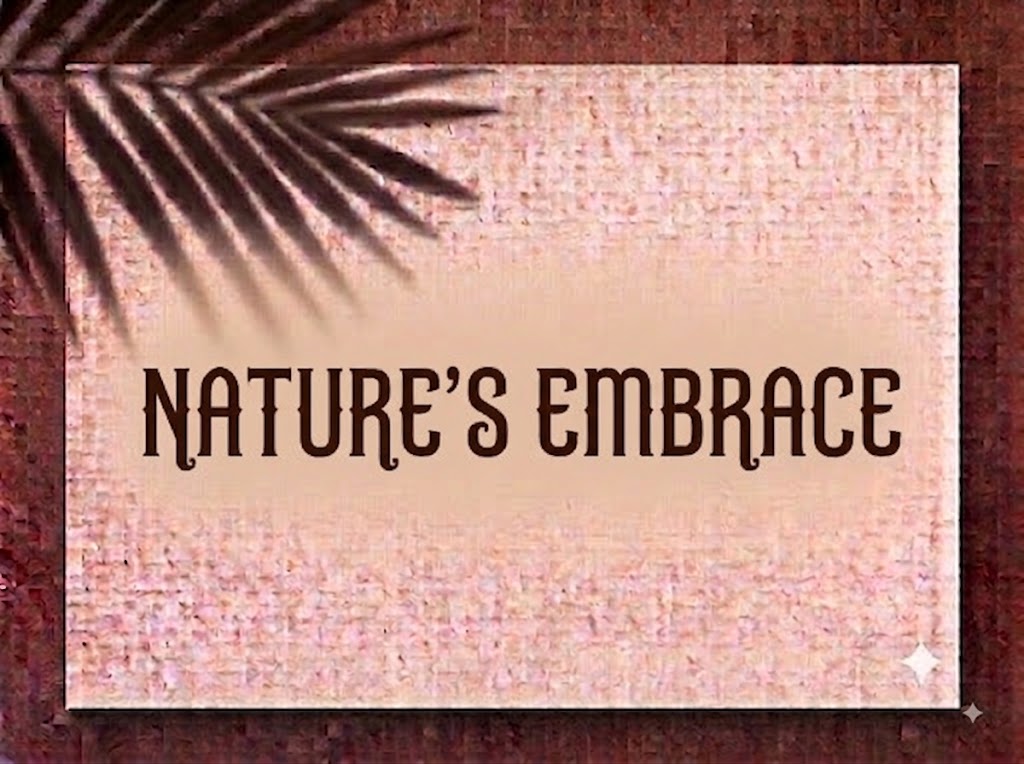
1FTV VIP Brownstone
Trong thế giới thiết kế đồ họa truyền thông và sáng tạo nội dung số, những bộ phông chữ Display mang phong cách Cổ điển (Vintage/Gothic) kết hợp các chi tiết gai nhọn (spur/thorn) luôn mang lại sức hút thị giác ấn tượng. Chúng tạo ra bầu không khí ma mị, huyền bí, đậm chất thần thoại hoặc hoài cổ cho các ấn phẩm nghệ thuật.
Nếu bạn đang tìm kiếm một phông chữ hiển thị độc lạ sở hữu các nét điểm xuyết sắc sảo để làm poster phim, thiệp mời Halloween, banner sự kiện hay tiêu đề video ngắn, font 1FTV VIP Brownstone chính là sự lựa chọn không thể bỏ qua.
Giới thiệu về font 1FTV VIP Brownstone
Font 1FTV VIP Brownstone là bộ chữ hiển thị trang trí (decorative display font) kết hợp giữa cấu trúc Serif cổ điển và nghệ thuật tạo hình chữ thời Trung cổ (Medieval/Gothic):
Tên phông chữ: 1FTV VIP Brownstone
Được hoàn thiện kỹ lưỡng về mặt kỹ thuật, phông chữ đem lại khả năng hiển thị vô cùng mượt mà. Bạn có thể tự tin phóng lớn chữ trên các ứng dụng đồ họa chuyên nghiệp hay phần mềm dựng video mà không lo gặp tình trạng vỡ nét hay răng cưa.
Đặc điểm nổi bật của phong cách thiết kế VIP Brownstone
Sức hút thị giác của font 1FTV VIP Brownstone nằm ở cấu trúc hình khối kiên cố cùng chi tiết biến điệu ký tự kịch tính:
Chi tiết điểm gai nhọn (Spur Accents) độc đáo: Điểm đắt giá nhất của phông chữ nằm ở các phần gai nhỏ nhô ra ở giữa thân chữ (như ở các ký tự
T,q,k,b,f,x,j,s…). Chi tiết này tạo nên cảm giác hoang dã, ma mị, gợi nhớ đến phong cách khắc gỗ cổ xưa hay kiến trúc Gothic huyền bí. -
Chân chữ Serif vững chãi & Cổ điển: Phần chân chữ và đường gạch ngang được tạo hình góc cạnh, giúp dòng tiêu đề luôn giữ được sự cân bằng, thu hút ánh nhìn từ khoảng cách xa.
Hỗ trợ trọn bộ chữ hoa và chữ thường: Phông chữ tích hợp đầy đủ hệ thống chữ cái in hoa, in thường cùng dãy số 0-9 phom dáng đồng bộ, giúp bạn dễ dàng phối hợp phân tầng nội dung cho thiết kế.
Khoảng cách giữa các chữ (kerning) và độ giãn dòng được tính toán chuẩn xác, giúp các chi tiết gai nhọn khi đứng cạnh nhau không bị dính nét hay gây cảm giác rối mắt.
Tích hợp trọn vẹn bộ chữ cái hoa – thường, dãy chữ số 0-9 phom dáng cá tính cùng hệ thống ký tự đặc biệt, dấu câu thông dụng.
Bản Việt hóa chuẩn chỉnh giúp bạn hoàn toàn yên tâm thiết kế các văn bản tiếng Việt có dấu phức tạp mà không gặp lỗi nhảy font hay mất ký tự.
Hình ảnh demo thực tế của font 1FTV VIP Brownstone
Khả năng hiển thị của phông chữ này được tối ưu rất tốt trên nhiều tỷ lệ kích thước khác nhau:
Kích thước nhỏ (12pt – 24pt): Cấu trúc nét chữ rành mạch giúp bộ chữ thường và dãy số vẫn hiển thị rõ ràng trên màn hình di động.
Kích thước lớn (36pt – 72pt): Đây là đất diễn lý tưởng nhất để 1FTV VIP Brownstone phô diễn toàn bộ sự ma mị, cổ điển của các đường gai điểm xuyết, tạo tác động thị giác mạnh mẽ cho các dòng tiêu đề chính.
Ứng dụng trong thiết kế đồ họa và làm video
Sở hữu nét cá tính hoài cổ và ma mị, font 1FTV VIP Brownstone mở ra không gian ứng dụng phong phú:
Video ngắn (TikTok, Reels, Shorts): Dáng chữ uốn nét gai hiển thị rất thu hút trên khung hình đứng tỷ lệ 9:16. Cực kỳ ăn nhập với các video kể chuyện kinh dị, review phim huyền bí, game nhập vai (RPG/Fantasy) hay vlog khám phá thiên nhiên.
Ảnh thu nhỏ YouTube (Thumbnail): Lựa chọn tuyệt vời cho các kênh làm nội dung về tâm linh, lịch sử, game fantasy, âm nhạc Rock/Metal hoặc storytelling nhờ giao diện độc lạ và gây tò mò.
Thiết kế Poster, Bìa sách & Event Halloween: Hoàn hảo cho các poster phim kinh dị, tiệc Halloween, bìa tiểu thuyết giả tưởng, triển lãm đồ cổ hay sự kiện âm nhạc indie.
Nhận diện thương hiệu Vintage & Streetwear: Thích hợp làm logo dạng chữ khối cho quán pub/bar, thương hiệu đồ da, tiệm xăm (tattoo shop), nhãn hiệu thời trang streetwear hoặc bao bì sản phẩm thủ công.